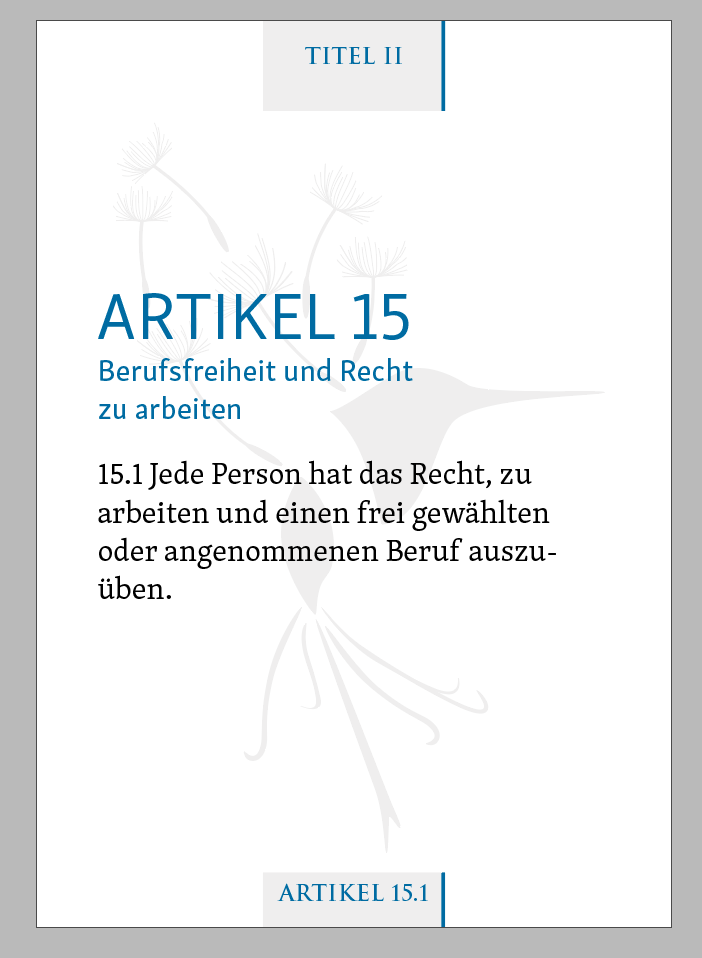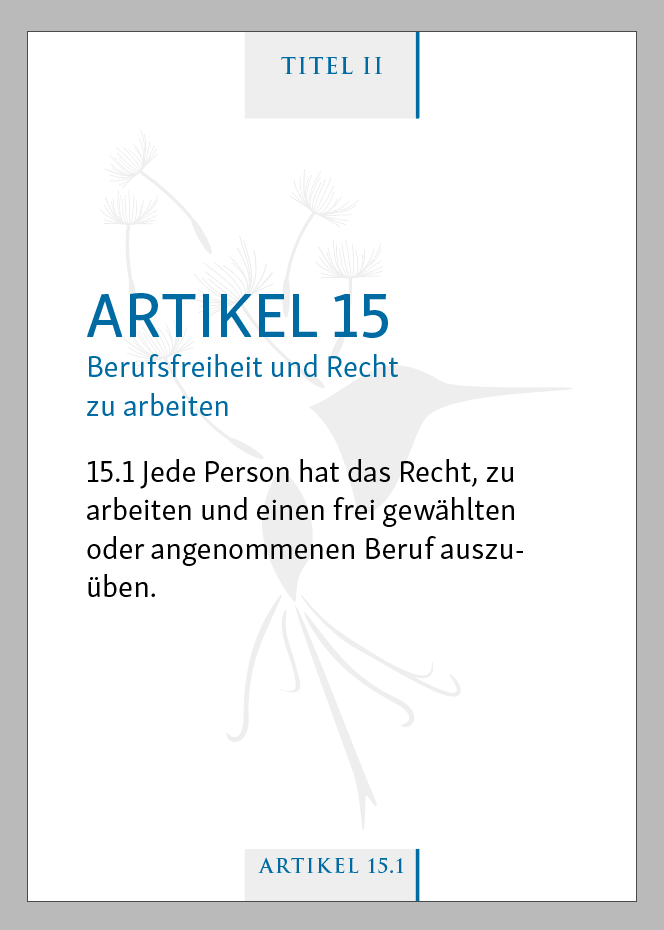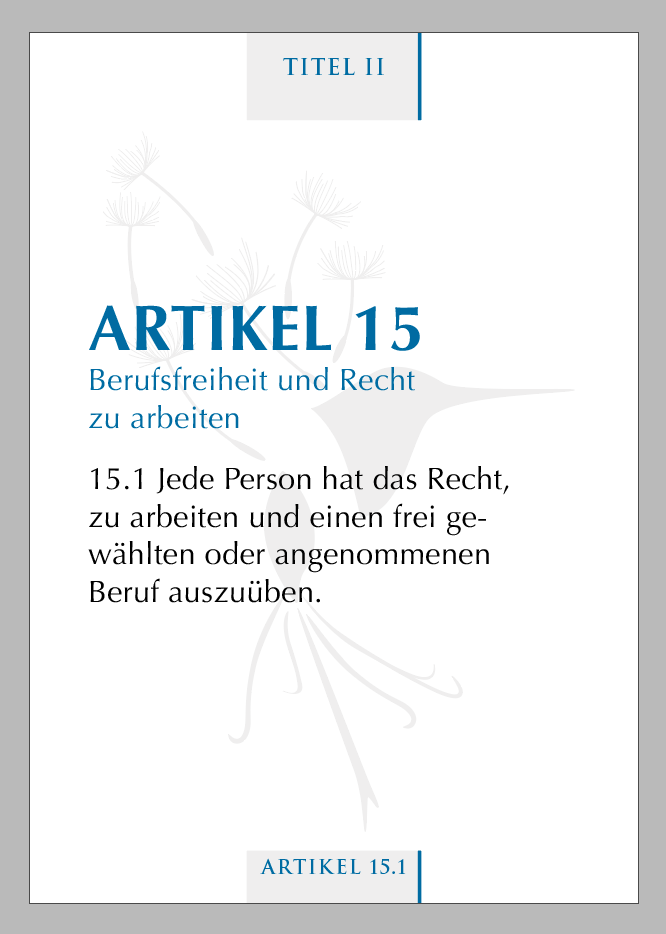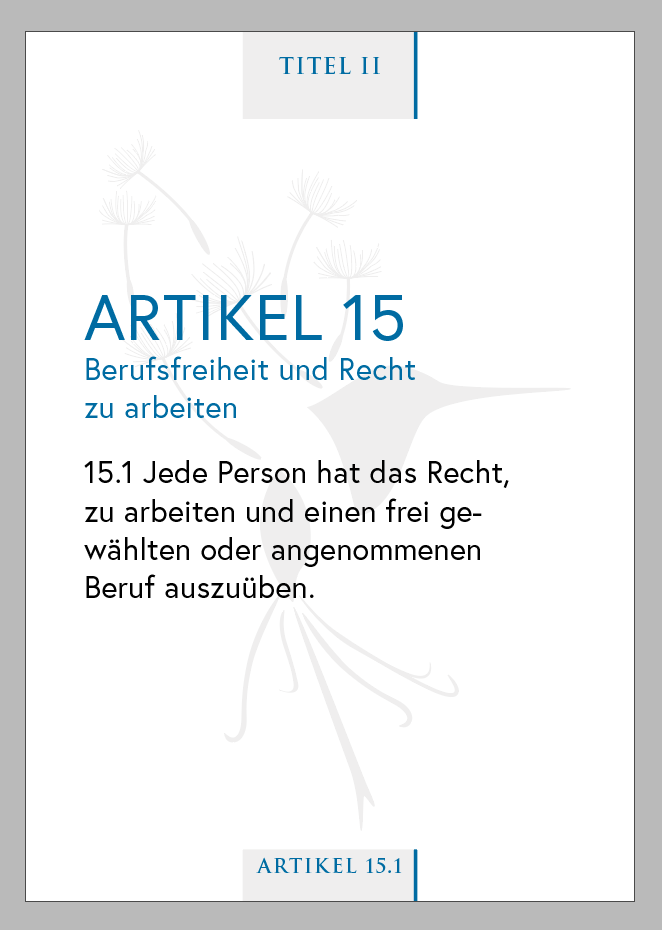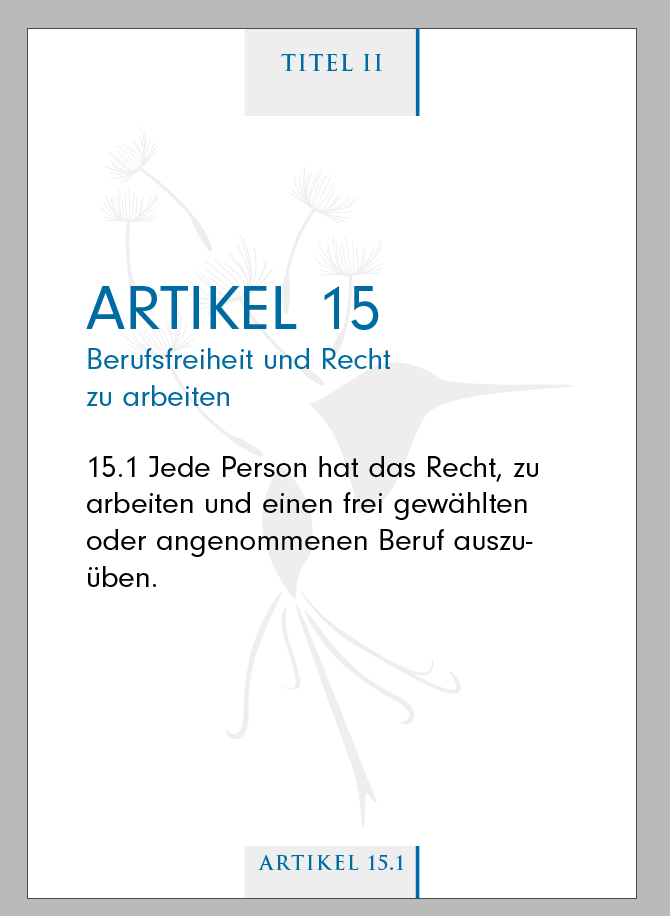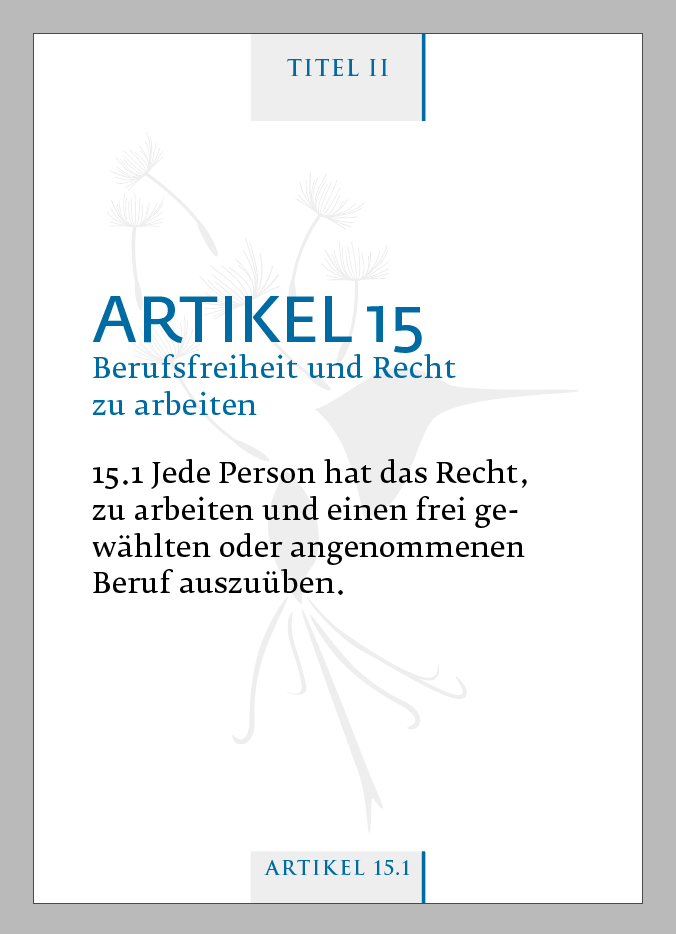
Fonts die miteinander Harmonieren / alle 27 EU Länder beinhalten
Zu deiner Frage bez. Welche Botschaft soll die Schrift vermitteln …
Headline, Subline und Fließtext
> Eine klare Botschaft vermitteln
> Recht
> Respekt
> Zuverlässigkeit
> Sicherheit
> Seriosität
> Professionalität
> Modern/traditionell (Sie soll jung, alt verbinden-egal woher du kommst)
> gute Lesbarkeit
> keine 0815 Schrift
> Eigener spannenden Charakter rüberbringen
Zielgruppe
> Jung und Alt
> Kinder, Jugendliche, Studenten
> Pädagogen: Lehrer, Professoren, Lehrende
> Bildungsinstitut: Mittelschule, Gymnasium, Sozial-Einrichtungen, Asyl-Einrichtungen
Spräche denn etwas gegen eine hervorragend ausgebaute Schriftsippe wie die Skolar, Fedra oder Thesis? Diese scheinen mir für das Thema und die Zielgruppen sehr gut geeignet zu sein. Und Du erhältst auch zwei Stile, welche ganz klassisch eingesetzt werden können: Sans für Überschriften, Serif für Mengensatz.
Und ich glaube, wenn man nicht bei „0815“ enden will, sollte man Google-Fonts schon mal ausschließen, ebenso wie Times, Calibri & Co. Aber das wäre meine Definition von „0815“. Wäre gut zu wissen, was Deine ist.
Oder wenn es günstig sein soll: PT Sans/Serif.
Und, irgendwie reizt mich die Idee, mir vielleicht auch mal die Corporate ASE angucken. Vielleicht kann man da ein wenig am Nimbus von Mercedes schmarotzen 😄
Auch wenn ich bei meinen drei Vorschlägen schon darauf eingegangen bin – vielleicht kann man ja inzwischen nochmal beleuchten, wie man diesen Aspekt bei der Schriftsuche generell gut herausfiltern kann:
Ich finde die größte Herausforderung ist Schriften zu finden, die alle 27 EU-Länder beinhalten.
Den Sprachfilter bei fonts.adobe.com in der linken Spalte finde ich dafür zwar wenig überzeugend, aber es wäre zumindest schon mal ein Ansatz.
Und, um die Sprachkompatibilität einzugrenzen, braucht es auch eine Definition der benötigten europäischen Sprachen: https://de.wikipedia.org/wiki/Amtssprachen_der_Europäischen_Union
Zum Beispiel soll Russisch und Türkisch berücksichtigt werden? Die gehören zwar nicht zu einer westlichen Idee von Europa, sind aber historisch, geographisch und tlw. auch politisch und kulturell nicht aus Europa wegzudenken.
widerspricht sich ggf. etwas mit
Da hat sicher jeder – wie beim Thema „0815“ auch – andere Maßstäbe, hier die Grenzen so auszuloten, dass die unteren Attribute noch ausreichend zum Tragen kommen. Aber das nur am Rande.
Hier noch ein paar nicht so häufig gemachte Vorschläge etwas neuerer Schriftsippen – nach unten hin eigenständiger:
Die Sprachunterstützung wird oft auch erst optimiert bzw. erweitert, wenn sich eine Schriftfamilie am Markt als erfolgreich erweist. Insofern wäre ein weiterer Rat, direkt bei der Foundry nachzufragen, solltest Du bzgl. Sprachabdeckung unsicher sein, Dir ein Vorschlag aber bzgl. der anderen Gesichtspunkte als geeignet erscheinen.
Hier finde ich fonts.at (in Wien) besser.
Bez. 0815 …Helvetica, Arial, Calibri, Times Roman, Google Font (Ausnahme bestätigt die Regel) und über Adobe ärgere ich mich die meiste Zeit schon.
@Phoibos: Ich danke dir für den Hinweis! Grundsätzlich würde ich die Trajan für die  Kopf.- und Fußzeile sehr gut finden. Sie bietet in einigen Bereichen eine dickere Strichführung, als die Playfair Display.
Leider vertritt Sie nicht alle Sprachen.
01_Trajan und Optima
Font Trajan Pro 3 - Semibold: Kopf.- und Fußzeile | 6,5 / 7
Optima - Bold: Headline | 21 PT
Optima - Regular: Subline und Fliesstext | 10 PT (hier würde ich auf 9,5 PT gehen)
Die Fedra sollte übrigens auch Versalziffern für die Artikel-Nummer enthalten.
Übrigens hat die Skolar (Sans) auch gewisse Ähnlichkeiten mit der noch relativ neuen Hausschrift der Bundesregierung. Da dürften ja, abgesehen von der Sprachabdeckung, ähnliche Kriterien wie bei Deinem Projekt eine Rolle gespielt haben.
Vielleicht hilft das noch etwas bei der Entscheidung – ganz egal in welche Richtung. 😉